Allograph
»Allograph« ist ein Terminus für Grapheme, die denselben Laut darstellen, aber eine voneinander abweichende typometrische oder orthographische Form bzw. Schreibweise aufweisen. Etymologisch aus dem Altgriechischen »allos« für »anders« und »graphein« für »schreiben«. Alternative Schreibweise: »Allograf«.
In der Linguistik beschreibt ein Allograph eine von mehreren möglichen Formen eines bestimmten Schriftzeichens, unterschiedliche bzw. alternative Schreibweisen desselben Phonems oder die unterschiedlichen Schreibweisen sprachlicher Ausdrücke.
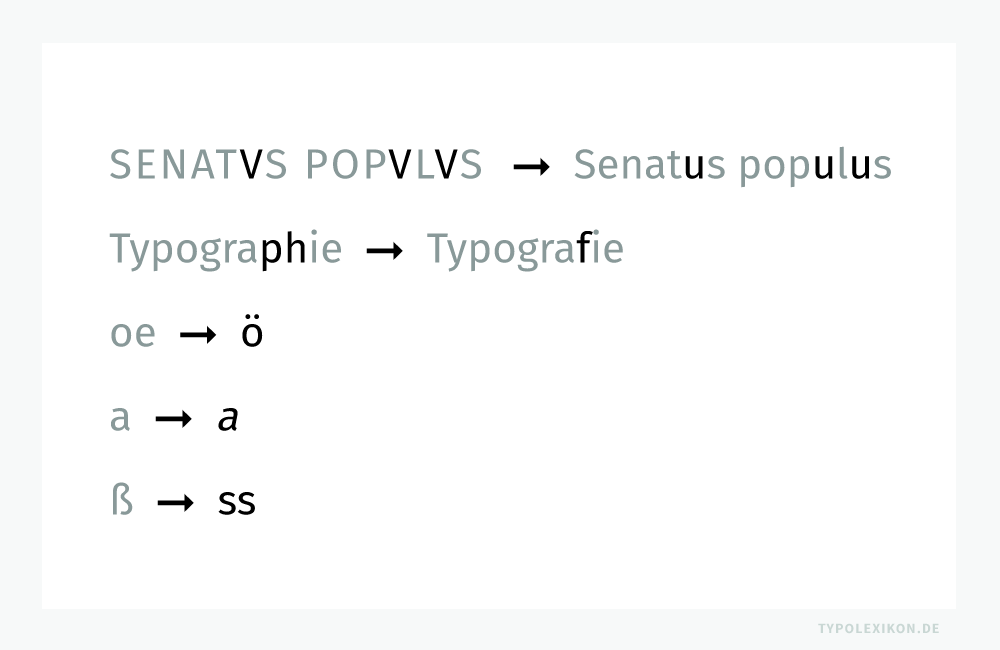
In der Typografie wird primär darunter die unterschiedliche Typometrie (Letternarchitektur) eines Zeichens – z.B. als Glyphe eines bestimmten Zeichens – oder die Formgebung eines Buchstabens in einem anderen Schriftschnitt, z.B. ein »a« im normalen Schriftschnitt im Vergleich zu einem »a« im kursiven Schriftschnitt, verstanden. Zur besseren Abgrenzung werden Varianten des gleichen Satzzeichens innerhalb einer Schriftfamilie oder Schriftsippe als Allographen, unterschiedliche Formvarianten eines Schriftzeichens innerhalb eines Schriftschnitts als Glyphen bezeichnet.
Die Typografie kennt unterschiedliche Arten von Allographen:
-
- Grapheme, die sich im Lauf der Schriftgeschichte verändert haben. So der Wechsel der Buchstaben »I« zu »J« und »V« zu »U«. Beispiel: »SENATVS POPVLVS« zu »Senatus populus«.
- Orthographisch reglementierte Grapheme. So die verschiedenen Schriftzeichen und Zeichenkombinationen für s-Laute (s, ss, ß) oder f statt ph. Beispiel: »Typographie« und »Typografie« oder »Allograph« und »Allograf«.
- Typografisch reglementierte Grapheme ohne funktionale Veränderungen, die lediglich unterschiedliche periphere grafische Merkmale im Schriftstil und im Figurenverzeichnis aufweisen, z.B. »a« zu »a«.
- Die »Auflösung« (Transformation) der Minuskelligatur »ß« (Eszett) im normalen Schriftstil zu »SS« in der Formvariante der Kapitälchen bzw. Majuskeln. Beispiel: »mußte« zu »MUSSTE«.
Begriffsabgrenzung
Ein »Graphem« ist die kleinste grafische Einheit eines Schriftsystems oder eines schriftähnlichen Zeichensystems. In der Regel handelt es sich hierbei um einen einzelnen Buchstaben oder um ein Schriftzeichen. Mehrere Grapheme, die innerhalb eines Schriftsystems die gleiche Funktion erfüllen bzw. die gleiche Bedeutung haben und einander ersetzen können, bezeichnet man als »Allographe«.
Jede Klasse von Allographen bildet wiederum ein Graphem. Beispielsweise fasst das Graphem »ö« mehrere Allographe zusammen. Beispielsweise hatte das heute gebräuchliche »ö« früher die Gestalt »oe«, »oͤ« oder »o̎«. Es könnte außerdem wie »ō«, »õ« oder »ő« aussehen, in anderen Sprachen auch wie »œ« oder »ø«. 1)
»Glyphen« hingegen sind konkrete Schriftzeichen innerhalb eines Schriftschnitts, beispielsweise Buchstaben (z.B. A, b, c), Buchstabenvarianten (z.B. geschlossenes »a« statt offenes »a«), Interpunktionszeichen (z.B. Anführungszeichen) oder Sonderzeichen (z.B. Pluszeichen). Der Begriff »Glyphe« wird in der Typografie also primär im Zusammenhang mit der Typometrie von Schrift- und Satzzeichen verwendet.
Irrungen und Wirrungen bei der Begriffsabgrenzung
In der Regel entspricht eine einzelne Glyphe einem einzelnen Graphem, wobei eine Glyphe zwar in der lateinischen Schriftkultur ein Graphem ist, jedoch kein Allograph sein muss. Eine Glyphe kann aber auch mehrere Grapheme enthalten. Beispiel: Die Graphfolge »oe« kann als Ligatur »œ« angelegt sein – also als eine eigenständige Glyphe bzw. typografische Ligatur dargestellt werden.
Andererseits kann eine Glyphe auch nur ein Teil eines Graphems sein. Zum Beispiel kann das Graphem »ö« aus einer Glyphe für den Buchstaben »o« und einer Glyphe für die Umlautpunkte »¨« zusammengesetzt werden. Normalerweise wird jedoch die Glyphe »ö« verwendet. In der Schriftlinguistik sind Grapheme darüber hinaus auch abstrakte Einheiten, um einen Bedeutungsunterschied in Wortpaaren zu markieren.